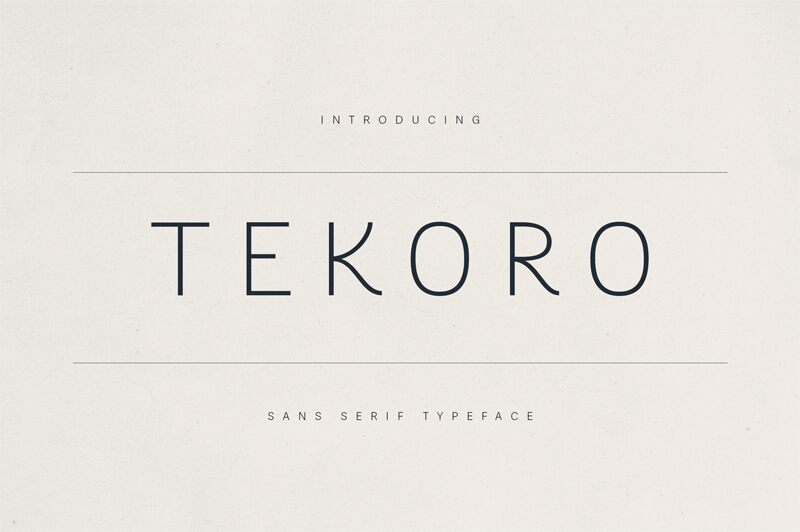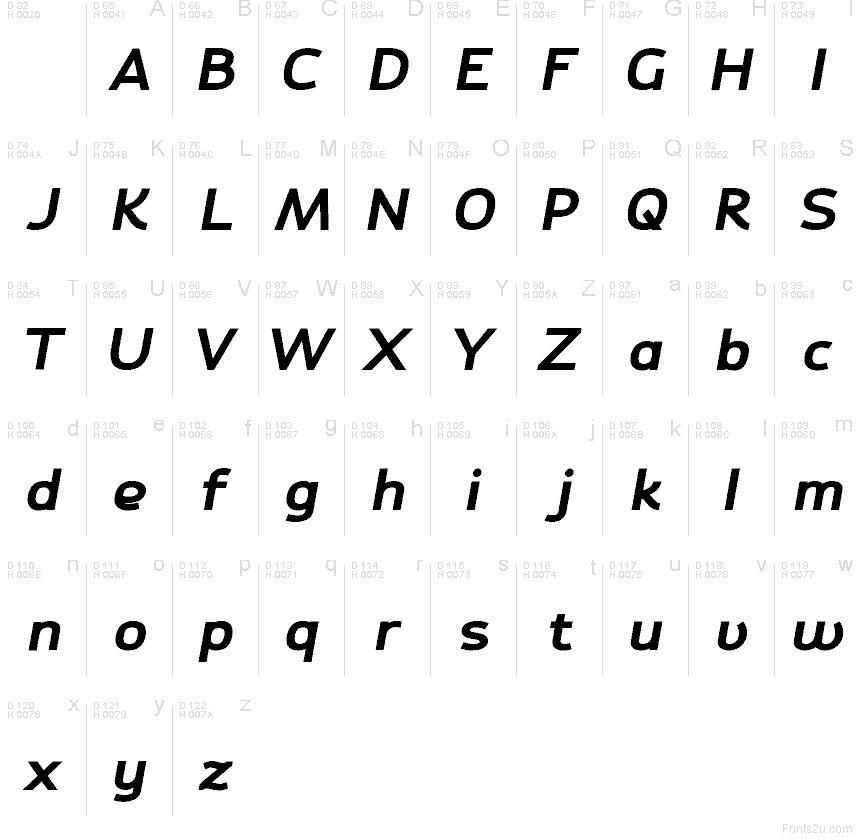
Tekoro Demo Black Italic
Tekoro Black Italic ist eine kostenlose, geneigte serifenlose Schrift mit einer breiten, flachen Silhouette, die ihr ein dynamisches, vorwärtsgerichtetes Erscheinungsbild verleiht. Die abgerundeten Kurven wirken voll und weich, während die scharfen Diagonalen für einen präzisen Kontrast sorgen – das macht den Entwurf zu einem stromlinienförmigen Display-Stil, der weit über eine neutrale Sans hinausgeht.
Diese Kombination aus sanften Rundungen und hartkantigen Verbindungen macht sie zur idealen Wahl für prägnante Überschriften auf Postern, Sportgrafiken, Album-Covern, Spieletiteln oder Verpackungen. Tekoro Black Italic verleiht zudem Logos und Social-Media-Bannern das gewisse Etwas, besonders wenn ein kompaktes, schnelles und kraftvolles Schriftbild gefragt ist.